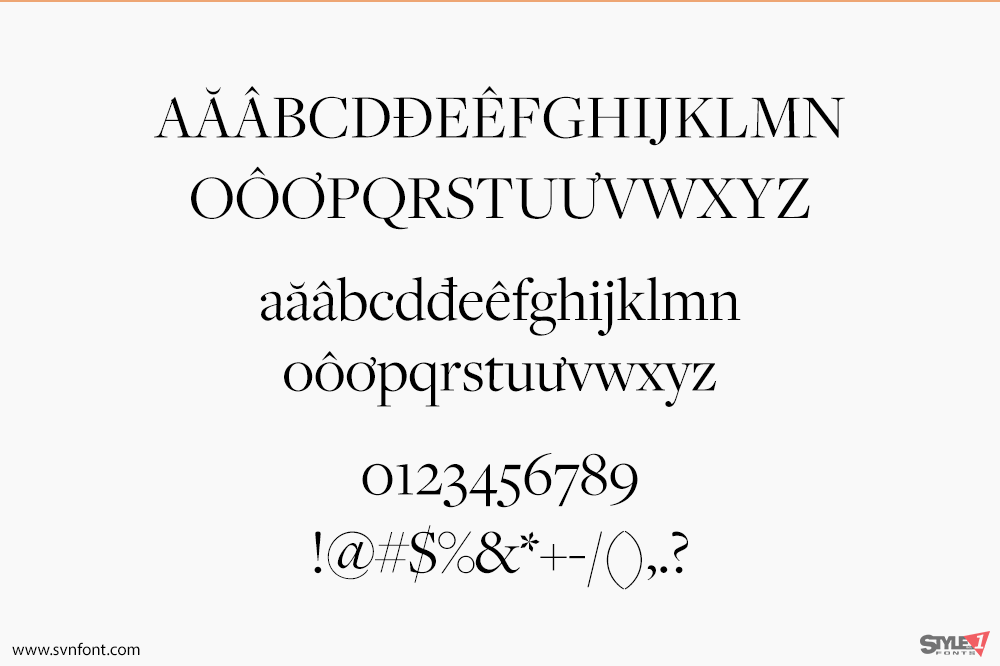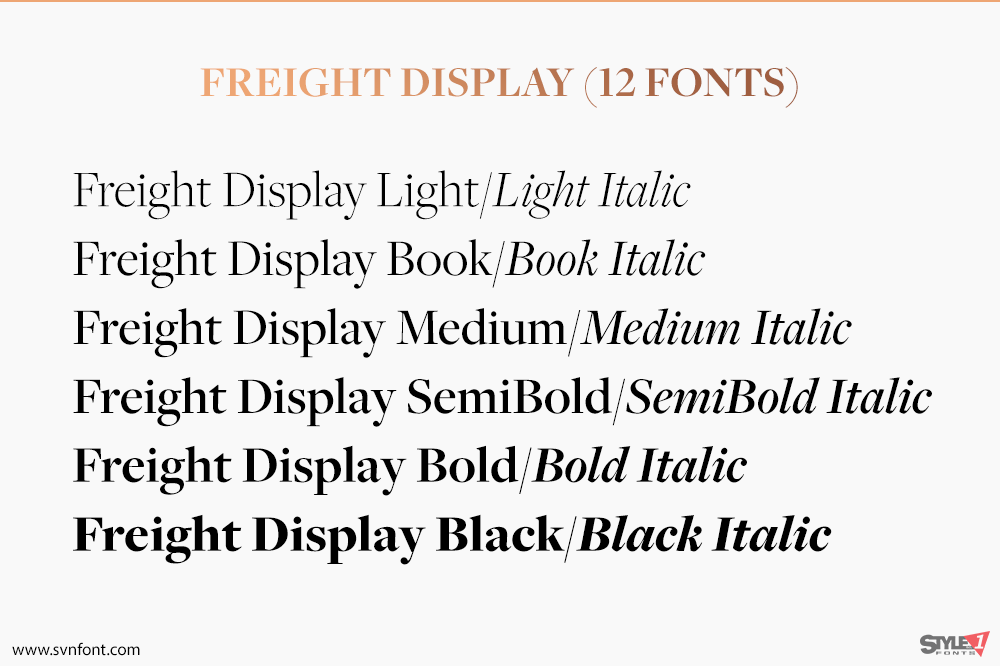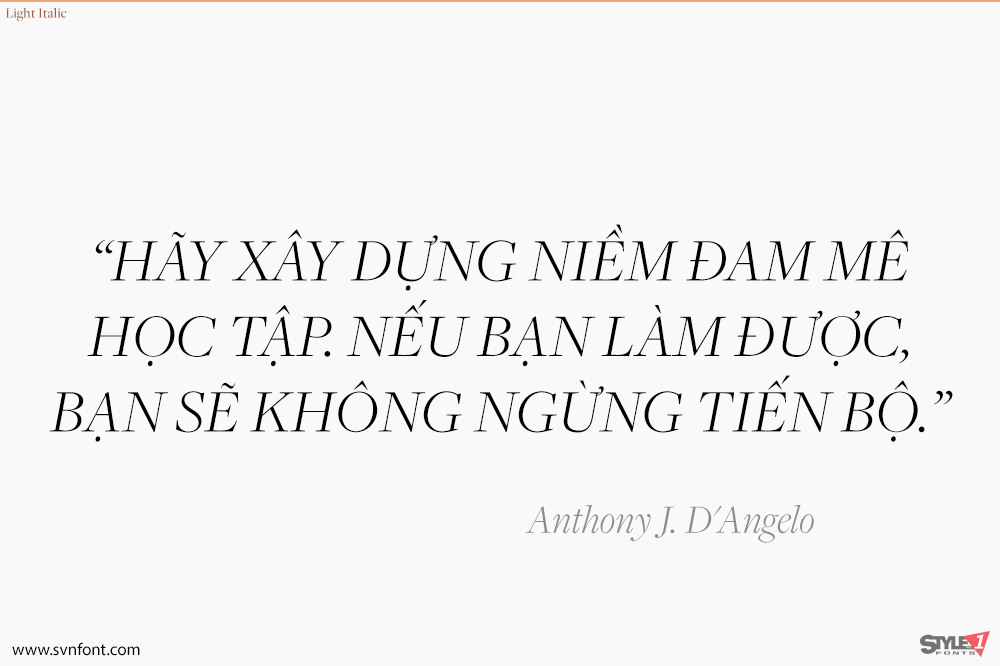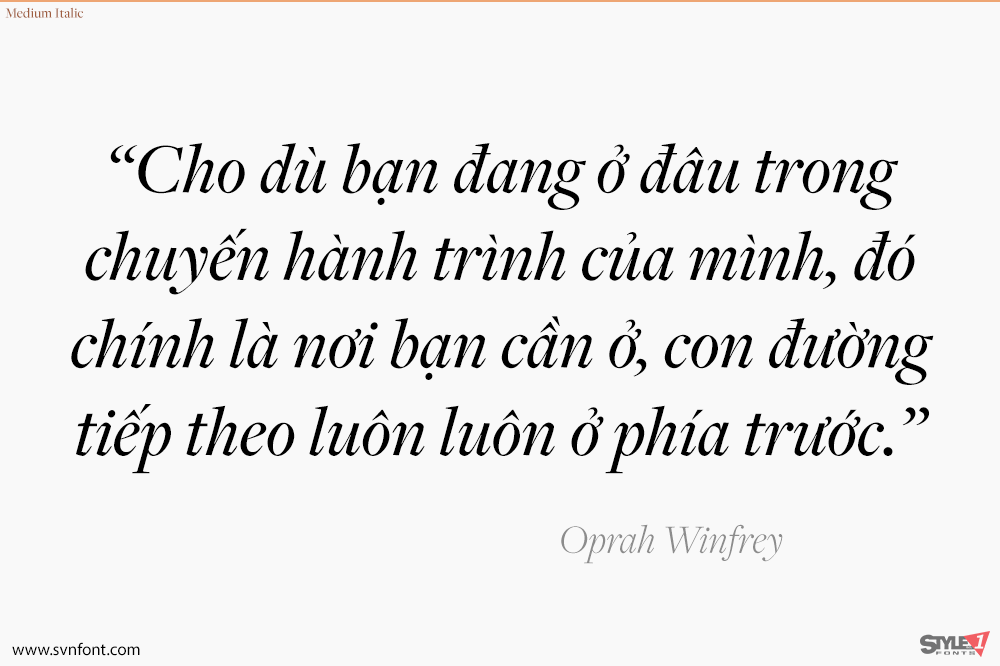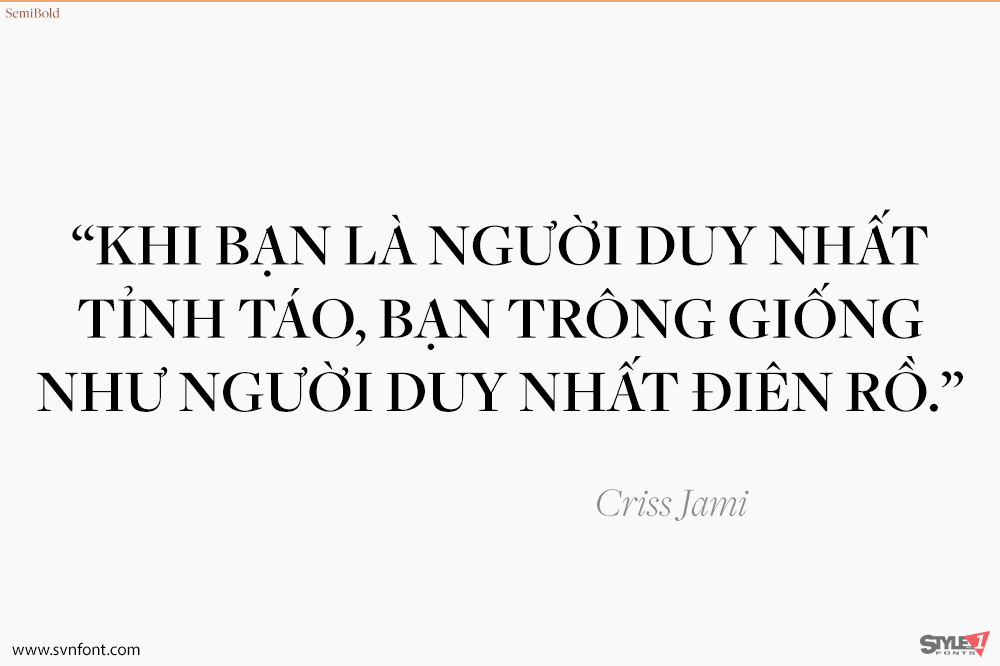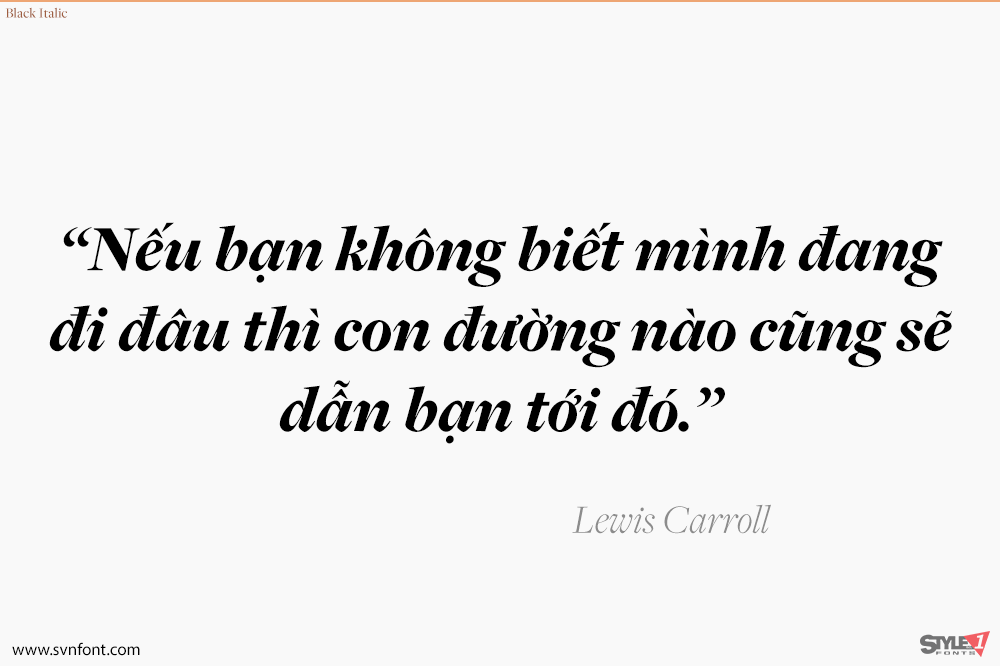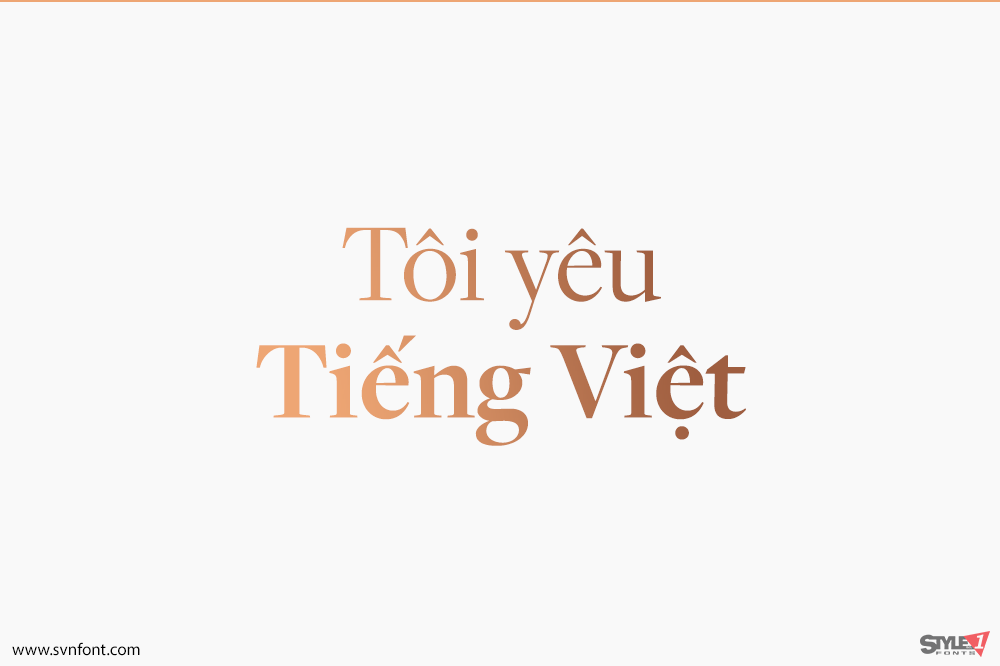
Freight Display nâng cấp từ bộ phông Freight Text với các khoảng trống mở hơn và độ tương phản cao hơn một chút. Những tỷ lệ ấm áp đó mang lại sự cân bằng cho các tiêu đề chính, tiêu đề chạy và tiêu đề phụ dễ đọc, đồng thời vẫn nổi bật khi được in đảo màu ở các kích thước nhỏ hơn.
Nhà thiết kế: Joshua Darden
Nhà phát hành: GarageFonts